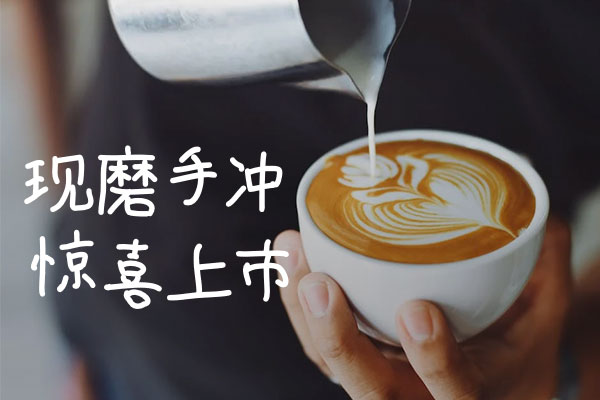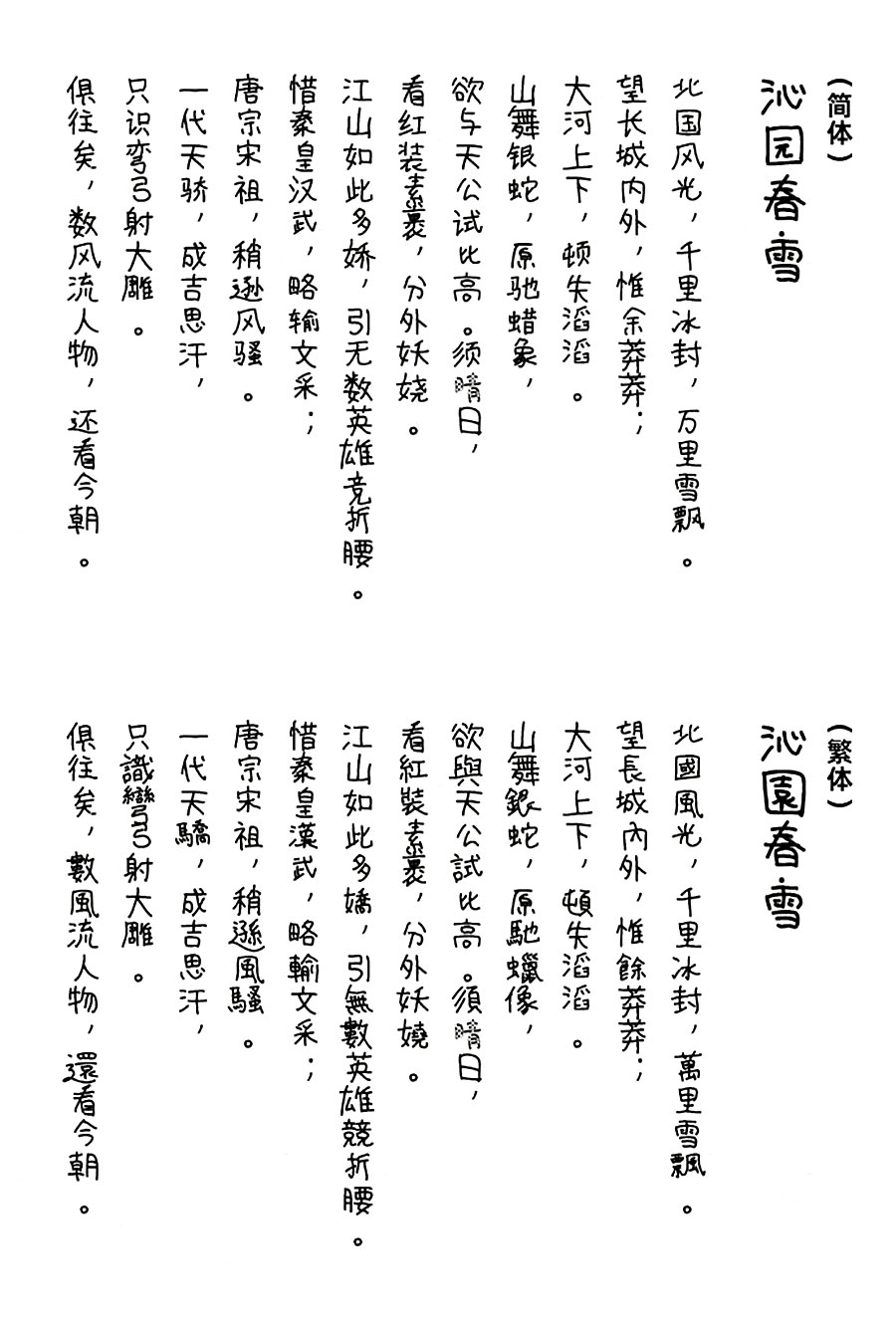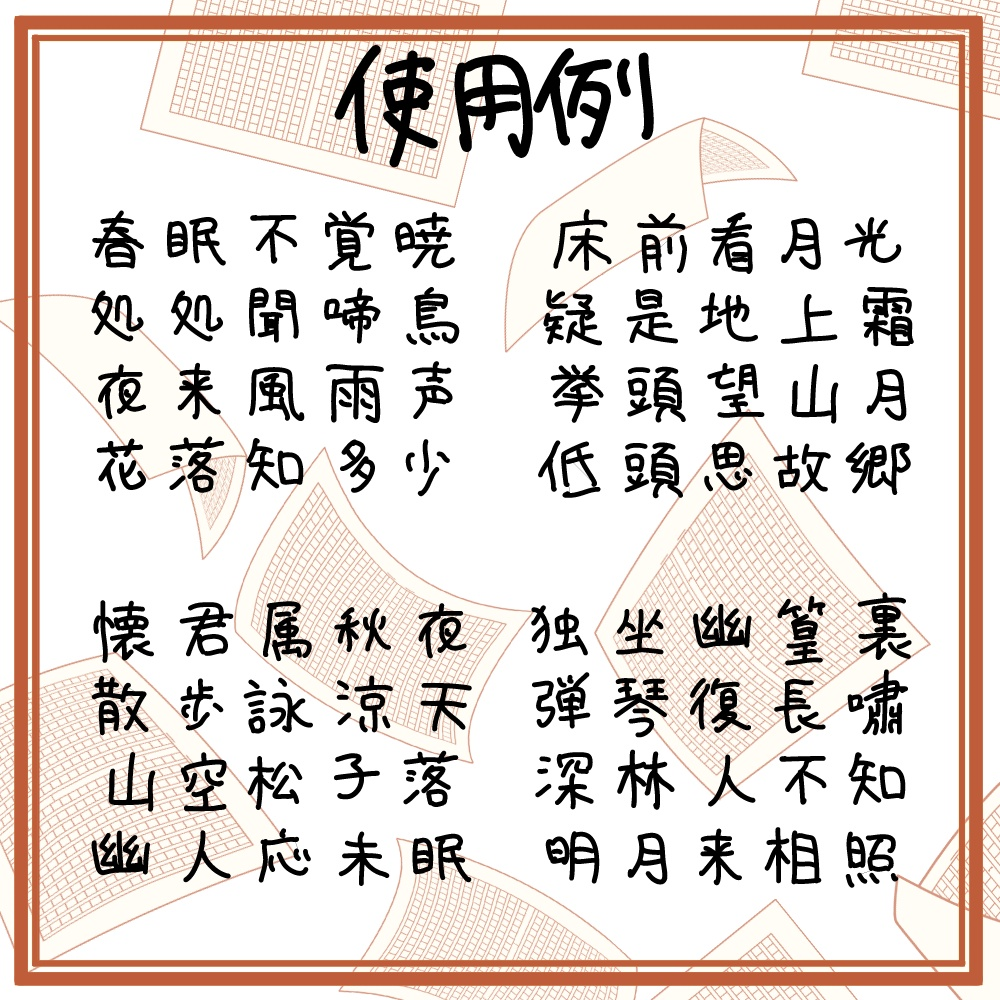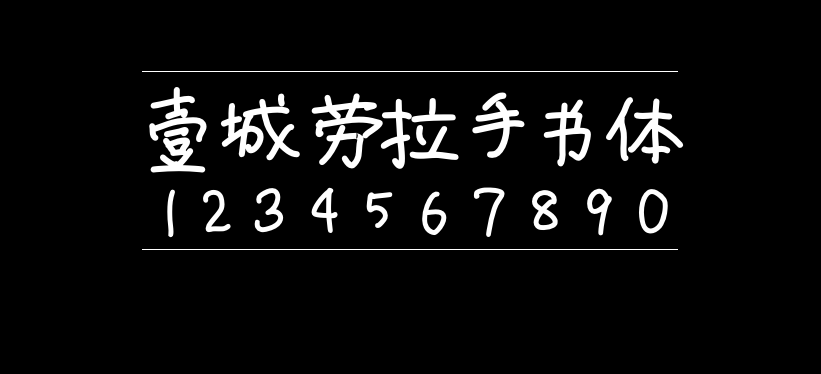
壹城劳拉手书体
壹城劳拉手书体(壱城ラウラフ font)是一款日系免费商用字体,首发于BOOTH网站,虽然该字体是日本推出的,但是它对简体、繁体的支持都非常好,基本没有缺字,大家可以放心使用。
壹城劳拉手书体
以下是该字体发布说明的原文引用:
Vtuber壱城ラウラの手書きのフォントです。
基本ラテン文字/ひらがな/カタカナ/JIS漢字水準に対応。
一部キリル文字とか。